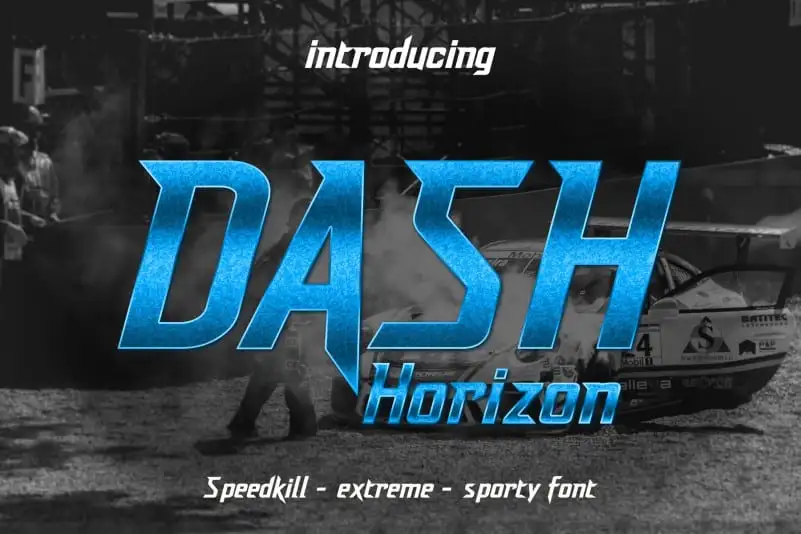
Dash Horizon Display Font – Download Grátis
A Dash Horizon Display Font é uma escolha perfeita para aqueles que procuram um estilo assertivo e moderno. Com sua tipografia agressiva e robusta, essa fonte atende à necessidade de grandes títulos e elementos visuais impactantes. Ela foi criada por Krisna Teja e é conhecida por sua precisão em criar um impressionante visual para suas aplicações. Seja no design de logotipos, blogs ou textos altamente acentuados, essa fonte de display se destaca pela sua forte presença na tela, o que a torna perfeita para os elementos que precisam chamar atenção imediatamente. Um exemplo de seu uso é uma frase chamando para um blog ou uma página web: “A Dash Horizon Display Font oferece estilos robustos e modernos, ideal para destacar títulos grandiosos em sua próxima publicação.”